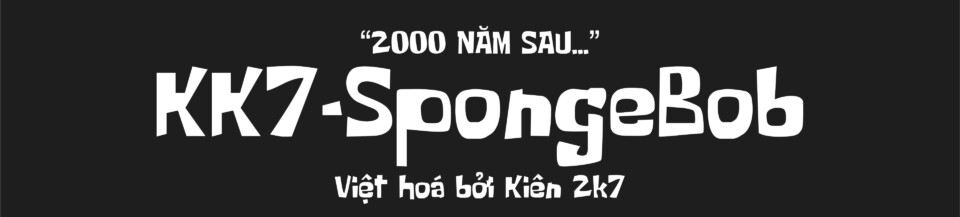
Giới thiệu về Font Việt Hoá KK7-SpongeBob
Trong thế giới đồ họa dành cho trẻ em, việc lựa chọn một Font Chữ phù hợp đóng vai trò cực kỳ quan trọng để truyền tải tinh thần vui nhộn. Font Việt Hoá KK7-SpongeBob là một bộ phông chữ độc đáo, lấy cảm hứng từ bộ phim hoạt hình SpongeBob SquarePants nổi tiếng. Với những đường nét uốn lượn, phá cách và mang đậm tính nghịch ngợm, bộ font này đã nhanh chóng trở thành lựa chọn hàng đầu cho các dự án thiết kế học đường và giải trí tại Việt Nam. Phiên bản việt hóa giúp người dùng dễ dàng sử dụng các ký tự đặc trưng mà không lo lỗi hiển thị.
Đặc điểm nổi bật của bộ Font Việt Hoá KK7-SpongeBob
Phong cách thiết kế trẻ trung
Bộ Font Việt Hoá KK7-SpongeBob sở hữu cấu trúc chữ cái dày, đậm và có độ biến dạng tự nhiên như những bọt biển dưới đại dương. Điều này tạo nên cảm giác gần gũi, thân thiện và cực kỳ bắt mắt đối với các bạn nhỏ. Đây không chỉ là một phông chữ thông thường mà còn là công cụ giúp các thầy cô giáo trang trí lớp học thêm sinh động.
Tính ứng dụng linh hoạt trong giáo dục
Bạn có thể sử dụng bộ phông này để làm tiêu đề bài giảng, thiết kế thiệp mời sinh nhật hoặc tạo ra các biểu ngữ cổ động trong trường học. Nhờ quá trình tối ưu hóa, bộ chữ đảm bảo tính thẩm mỹ cao trên cả bản in lẫn trình chiếu kỹ thuật số.
Hướng dẫn sử dụng và kết luận